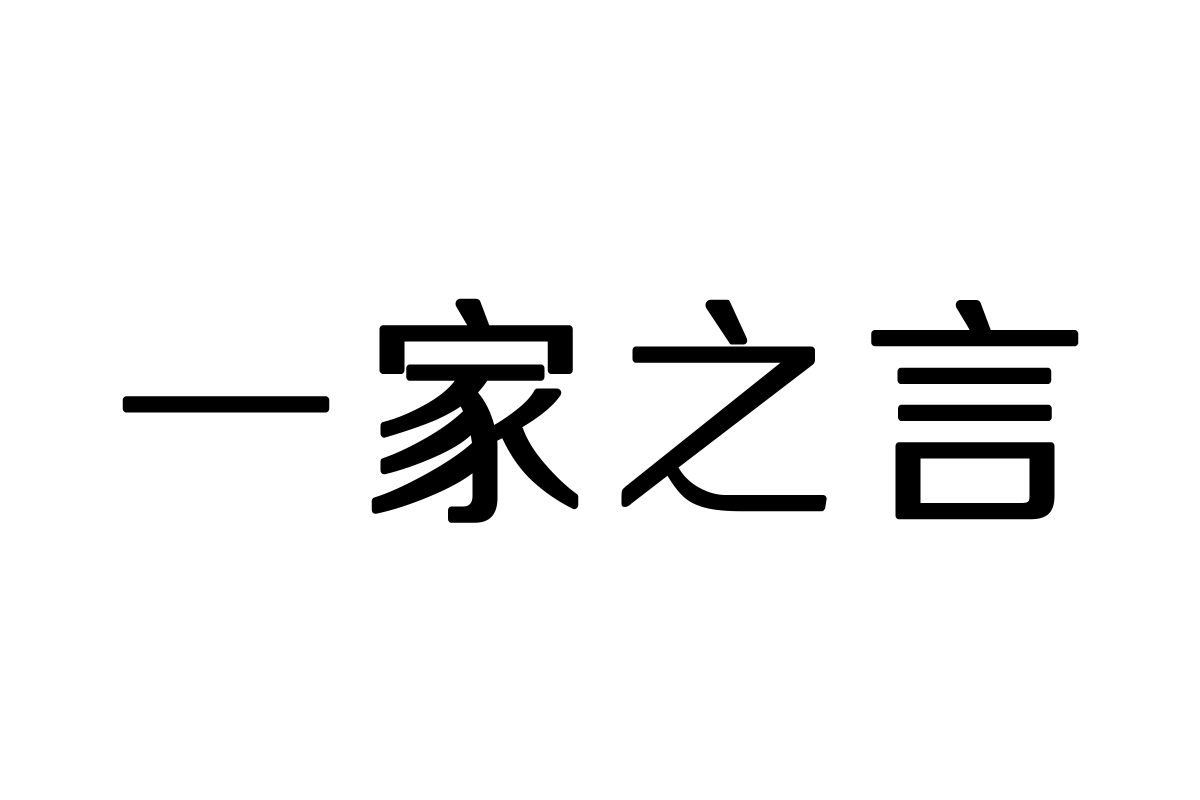
三极正极圆简体字体是一款具有独特设计特点的中文字体。它采用了简洁明了的字形结构,使得阅读起来更加清晰易懂。同时,该字体还注重了易读性和可读性,使得在不同场景下都能够展现出良好的视觉效果。
三极正极圆简体字体的特点在于其独特的字形结构和笔画处理方式。它的字形呈现出一种圆润、流畅的线条,使得文字看起来更加美观大方。此外,该字体还注重了字间距和行距的协调,使得整个页面布局更加和谐统一。
总之,三极正极圆简体字体是一款具有独特设计风格的中文字体,适用于各种应用场景,如广告设计、网页制作、书籍出版等。